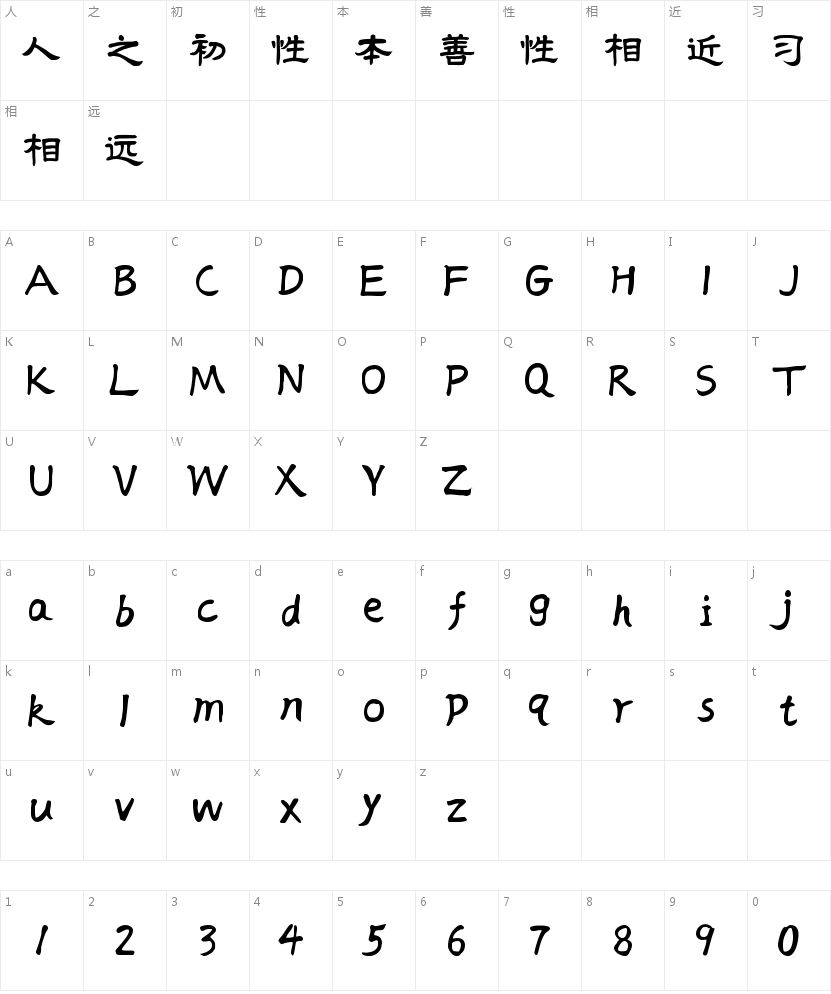
Aa放放隶书
Aa放放隶书是一款简约的行书字体,它的特点是落款和笔画粗细均匀,结构清晰、笔画简洁,在表达上既有着传统的古典感,又具有现代感。它的笔画粗细均匀,每一笔都是规整有序,笔画之间的距离也十分均匀,使得字体看起来更加简洁、大气,在视觉上具有良好的美感。
Aa放放隶书是一款非常不错的手写艺术字体,具有很好的视觉感,适合于文化类的宣传设计、商业类品牌的广告和产品包装设计以及个性化文字排版等较多场景。